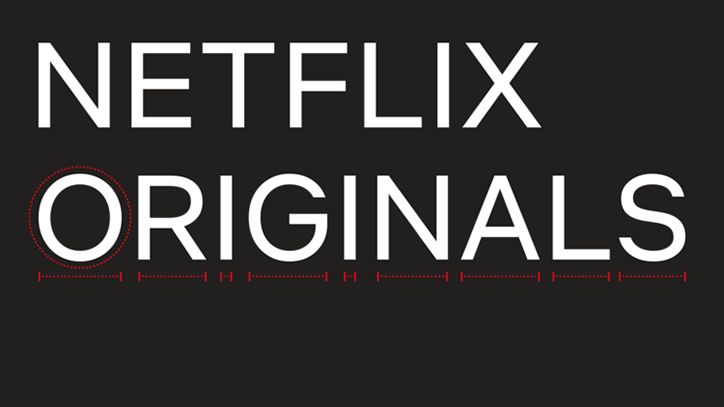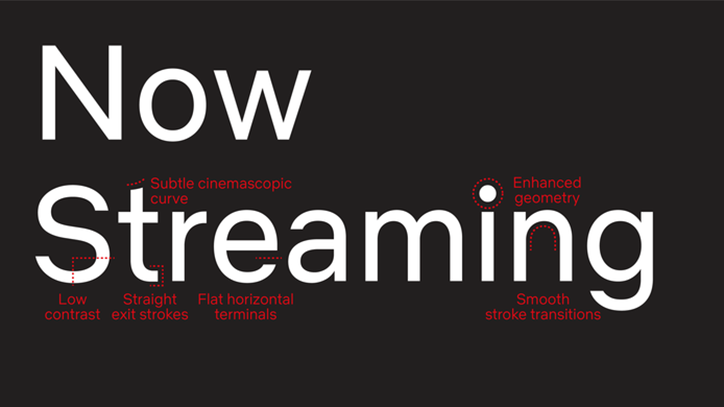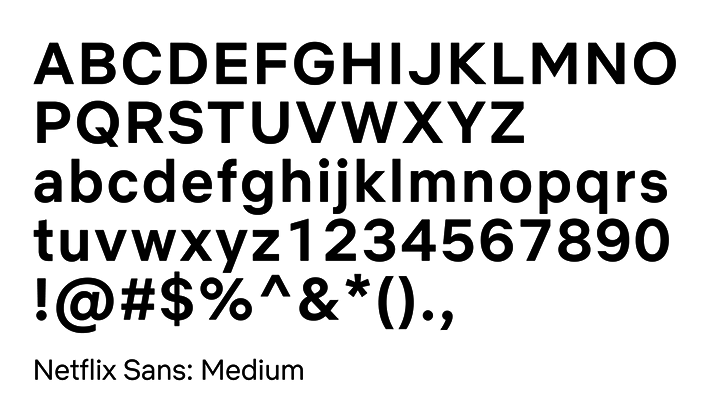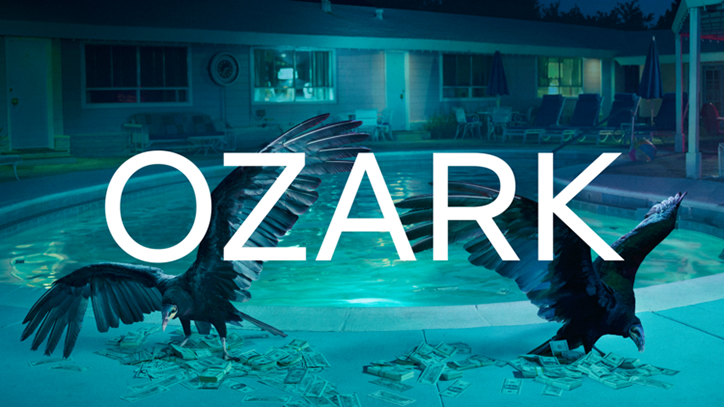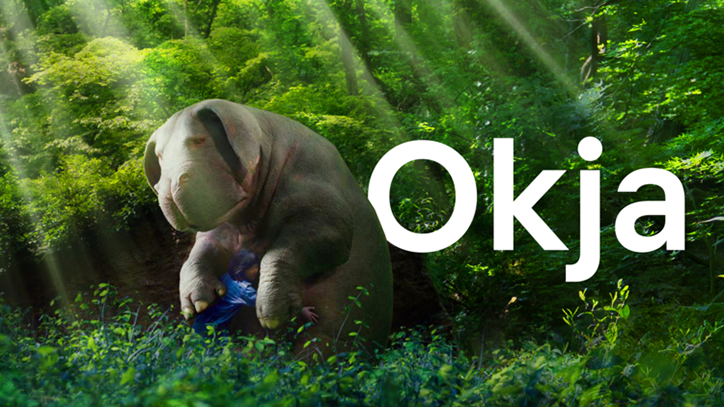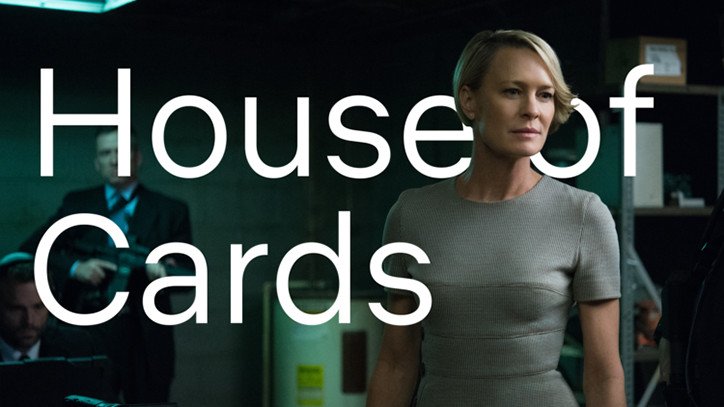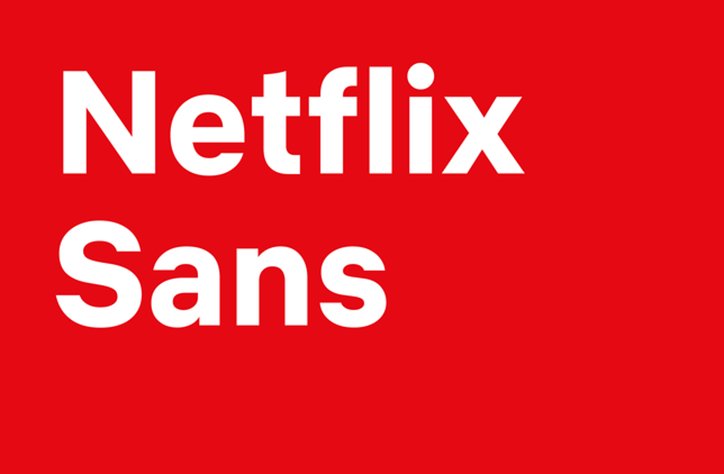
넷플릭스의 새로운 전용서체, Netflix Sans
온라인 동영상 스트리밍 서비스 기업 넷플릭스가 전용 폰트인 ‘Netflix Sans’를 출시했다. 애플(San Francisco), 삼성(SamsungOne), 구글(Roboro, Product Sans) 등 거대 IT기업들이 자체적으로 만든 전용서체를 사용해왔다는 점을 보면 넷플릭스 또한 명실상부 일류 IT기업의 반열에 오른 셈이다.
넷플릭스 브랜드 디자인팀 리더 노아 네이든(Noah Nathan)에 따르면, 기존에 라이선스 비용을 지불하고 사용했던 ‘Gotham’이라는 서체 대신 전용서체를 사용함으로써 넷플릭스는 브랜드 아이덴티티를 더욱 강화할 수 있게 되었으며, 연간 수백만달러의 비용 절감 효과를 거둘 수 있을 것으로 예상된다.
Netflix Sans는 디스플레이 화면에서의 미학적 구조와 실용성을 모두 고려하여 만들어졌으며, 대문자는 보다 ‘영화적’으로 보일 수 있도록, 소문자는 촘촘하고 효율적인 비율로 보여지도록 고안되었다. 노아는 서체의 디자인을 “접근하기 쉽고(approachable), 기하학적(geometric)인 그로테스크 스타일”이라고 묘사하며, 소문자 ‘t’를 아치 형태로 다듬은 것은 브랜드 워드마크의 “cinemascopic curve”에서 영감을 받은 것이라고 밝혔다.
이 프로젝트는 영국의 폰트 디자인 전문 기업 달튼 막(Dalton Maag)이 함께 했으며, 총 6개의 웨이트(regular, light, thin, medium, bold, black)로 제작되었다.